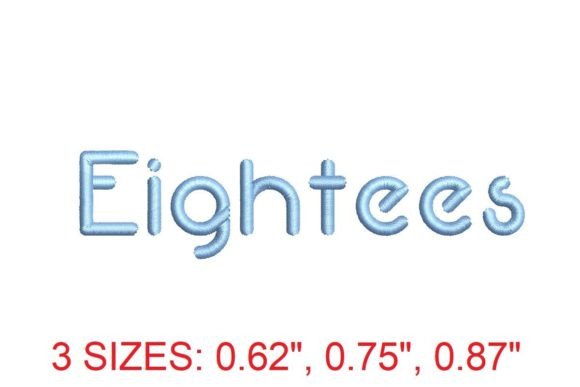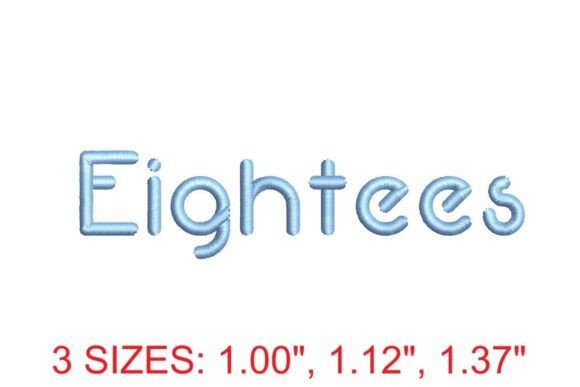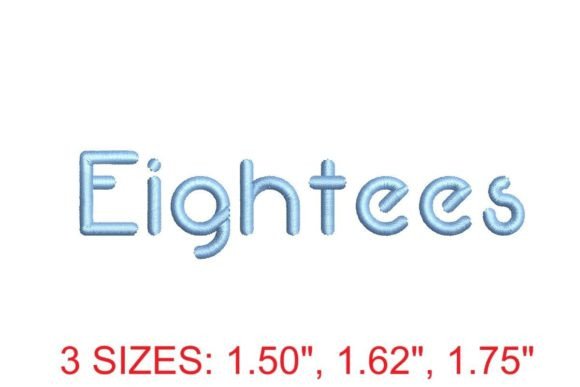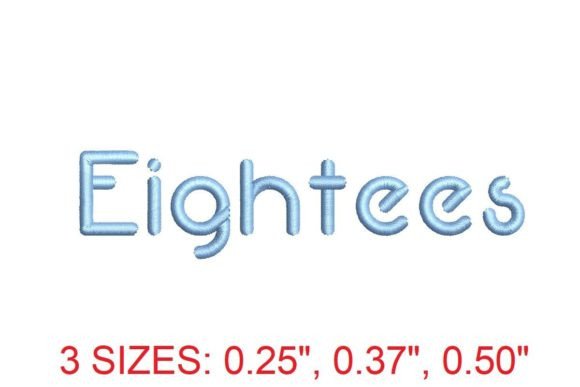
Eightees Font
Eightees Font — це спеціалізований, машинно-готовий шрифт, розроблений виключно для використання в програмному забезпеченні Pes Machine (PEM), що використовується для створення та модифікації футбольних ігор серії Pro Evolution Soccer. Завдяки своїй унікальній конструкції, яка враховує обмеження пам’яті, роздільну здатність текстур та особливості рендерингу в старих версіях PEM, Eightees забезпечує чітке, стабільне та візуально гармонійне відображення літер у меню, табло, іменах гравців та інших UI-елементах без будь-яких артефактів або спотворень.
Якість збірки та технічні деталі
Для кого найкраще підходить цей продукт?
Як це порівнюється з конкурентами
На відміну від загальних шрифтів на кшталт PESFont Pro або UltraFNT, Eightees має спеціальну підтримку української кирилиці з правильними формами літер (напр., відмінне відображення Ґ і Ї), а не просто транслітерацію. Також він легший за розміром (менше 40 KB) порівняно з багатофункціональними аналогами (до 200 KB), що критично важливо для обмежених за пам’яттю PEM-проектів, де навіть 10 KB можуть вплинути на стабільність компіляції.